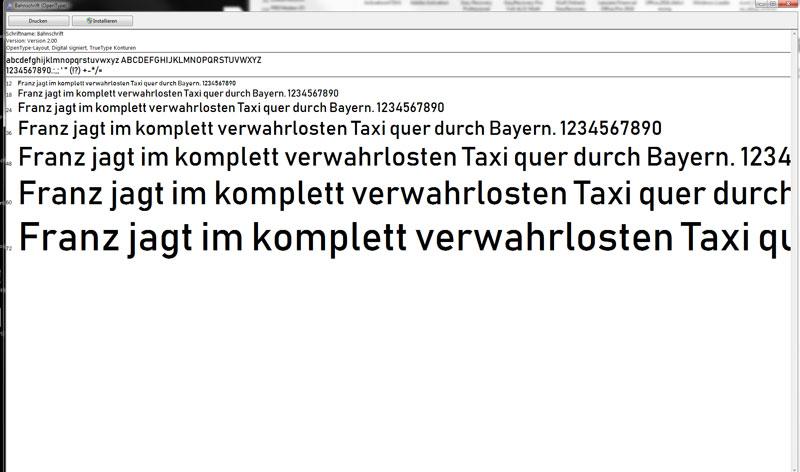
meine Frage betrifft das Kopieren eines Schriftschnitts von Win10 nach Win7. Und zwar ist in Win10 die Font "Bahnschrift" in einer Schriftfamilie gruppiert, in der alle Schriftschnitte beinhaltet sind.
Von der "Bahnschrift" würde ich gerne den Schnitt "Light" nach Win7 kopieren.
Gar nicht! Es sind nämlich nicht, wie sonst üblich für jeden Schriftstil ein eigener Font in Wondows10, sondern die Bahnschrift ist eine OpenType 1.8-Schriftart. Hier können in der einen Schriftdatei eben alle Schriftgewichte durch Interpolieren erzeugt werden (was den Light-Schnitt schon recht eierig wirken lässt, da der eben vom normalen Schnitt herunter abgemagert wird.)
Windows7 kann mit dieser Technik einfach nichts anfangen, und öffet die Schrift dann einfach nur in der Ausgangsform für die Interpolation der verschiedenen Schriftgewichte als normalen Schnitt.